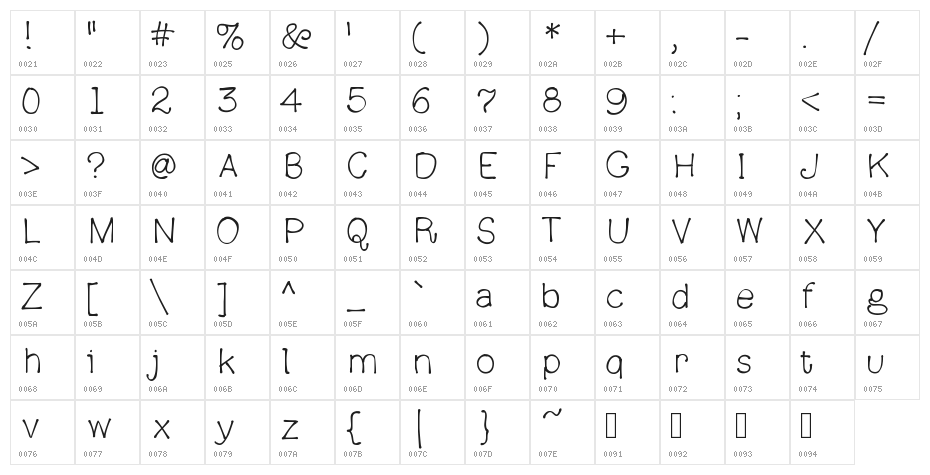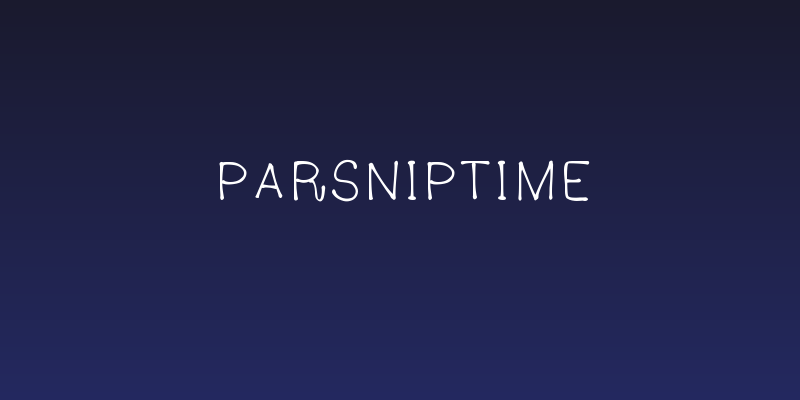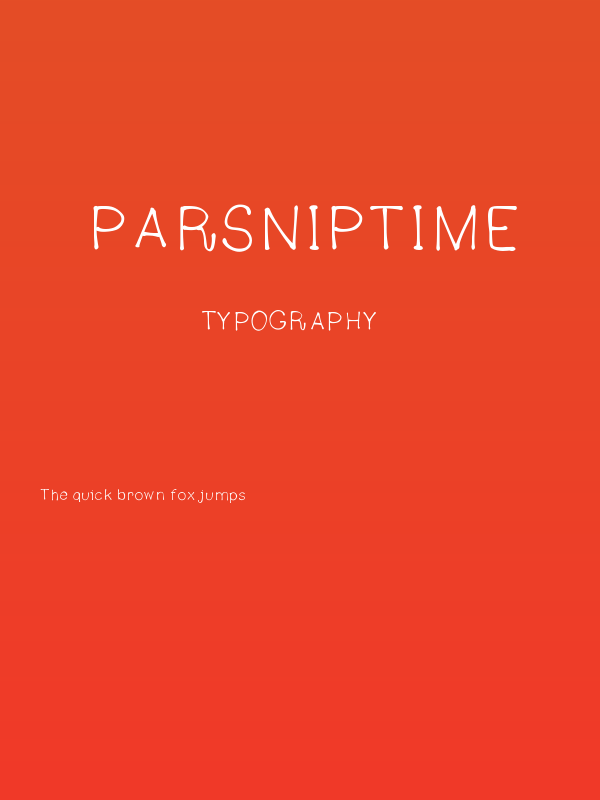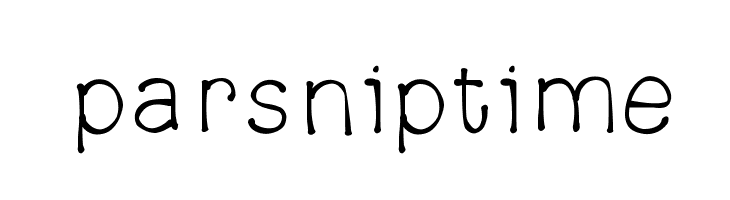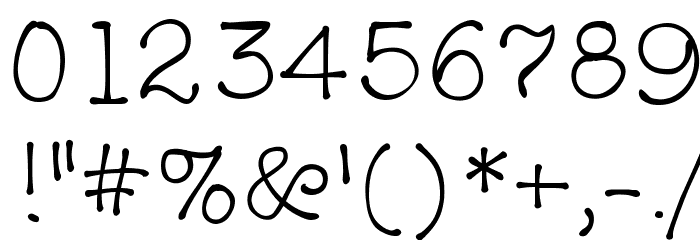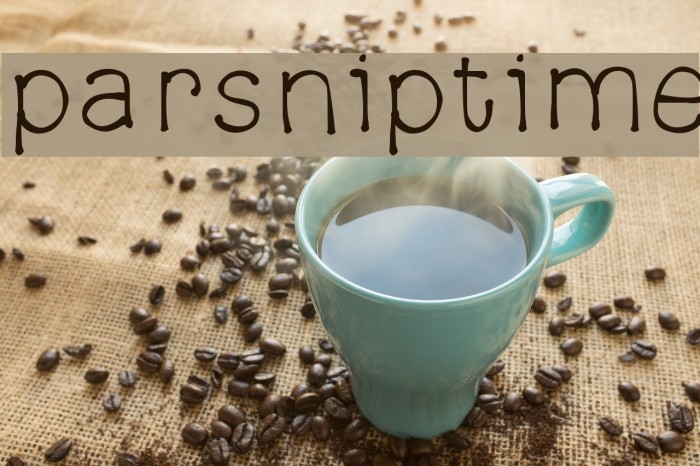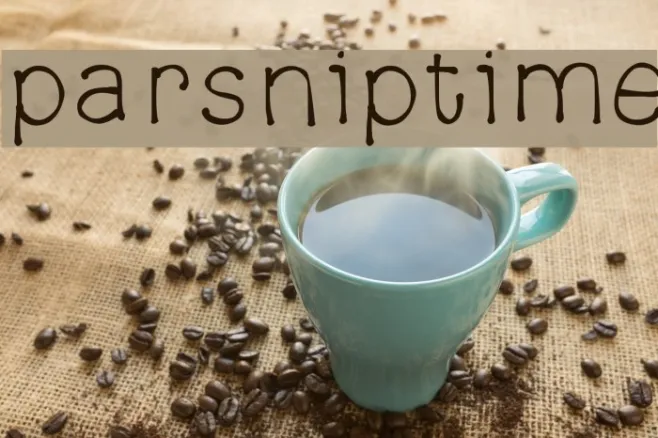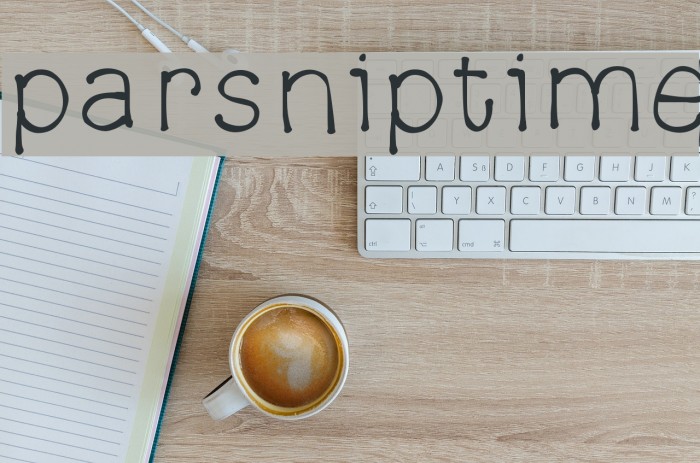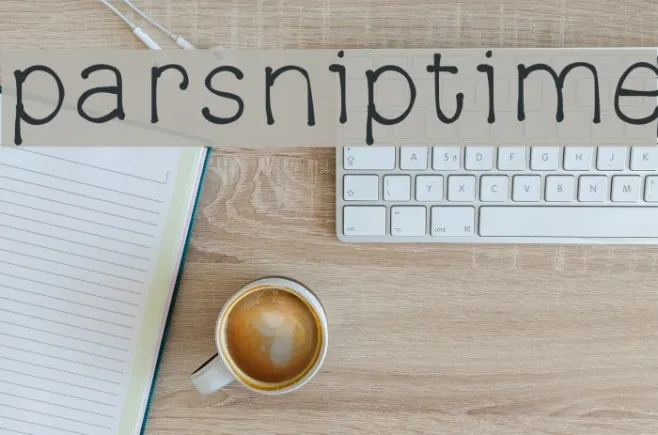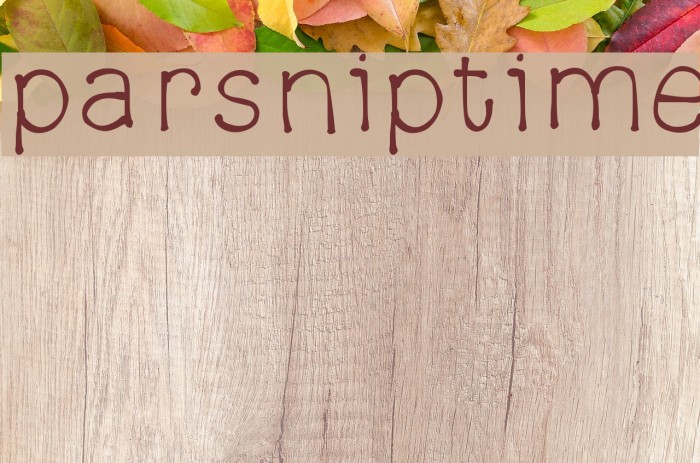
parsniptime Font
| Caso de uso | Headlines, Logos, Informal Text |
| Proyectos propuestos | Ideal for children's books, greeting cards, playful branding, and casual invitations. |